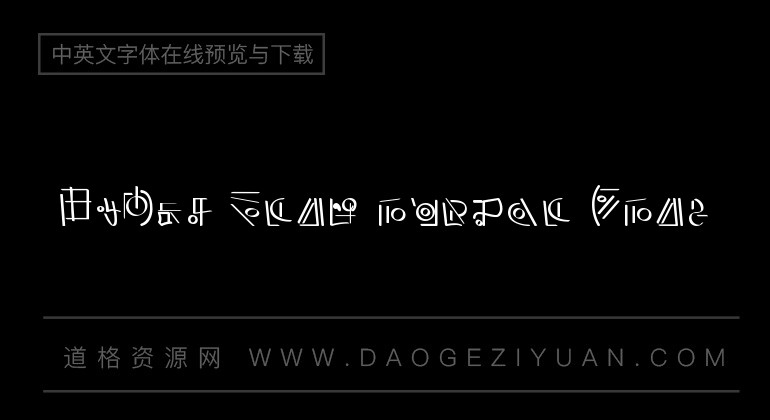
XiDus Lang ombwha Font 是一种装饰艺术字体,它的设计师是来自印度尼西亚的阿克茹·普拉塔玛。这个字体的设计灵感来源于印度尼西亚传统文化艺术和神话故事,因此它具有浓郁的印尼文化特色。 这种字体的特点是精细的装饰性花纹和曲线,每个字母都充满了艺术感和细节。它适用于印刷和数字设计,可以用于印刷海报、传单、名片、标志和网页设计等。它的特点是独特而华丽,是一种非常适合用于独特和富有创意的设计项目的字体。 总之,XiDus Lang ombwha Font 是一种精美的装饰艺术字体,它具有浓郁的印尼文化风格,适合于各种设计项目,是一种非常有用的字体。内容介绍
XiDus Lang ombwha Font是一款非常不错的手写艺术字体,具有很好的视觉感,适合于文化类的宣传设计、商业类品牌的广告和产品包装设计以及个性化文字排版等较多场景。